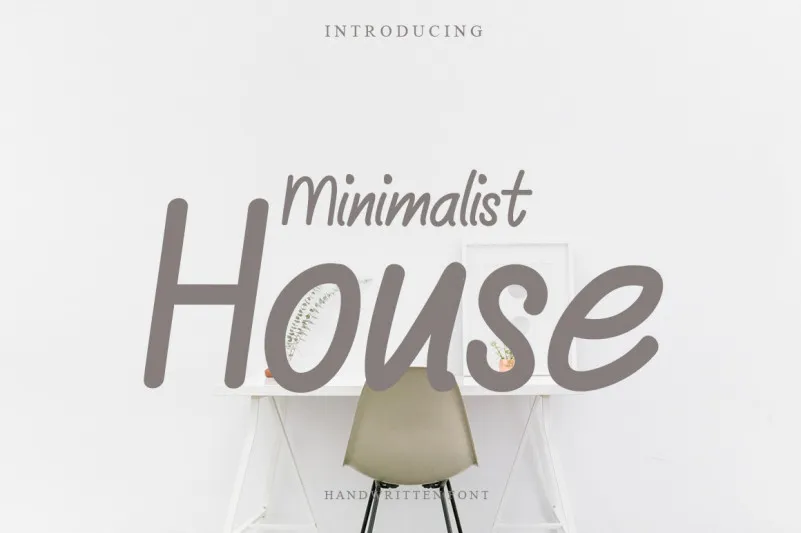
Minimalist House Font – Download Grátis
Esta é uma fonte escrita à mão que traz leveza e amabilidade. Suas características naturais e únicas a tornam perfeita para um vasto número de designs, desde logotipos até texturas personalizadas. Com sua natureza única, você pode explorar inúmeras variações dessa fonte linda e descobrir novos usos incríveis. Essa fonte apresenta uma versatilidade que permite que seu design seja interpretado de maneira diferente a cada nova aplicação. Experimente ela em diferentes texturas ou tamanho para criar ambientes dinâmicos, desde o suave até o robusto e tudo ao meio – ideal tanto para criações modernas quanto para um toque clássico. Engane-se se pensasse que o design de fontes só pode ser sério; essa fonte ‘Minimalist House’ é uma ótima maneira de brincar com o design visual.